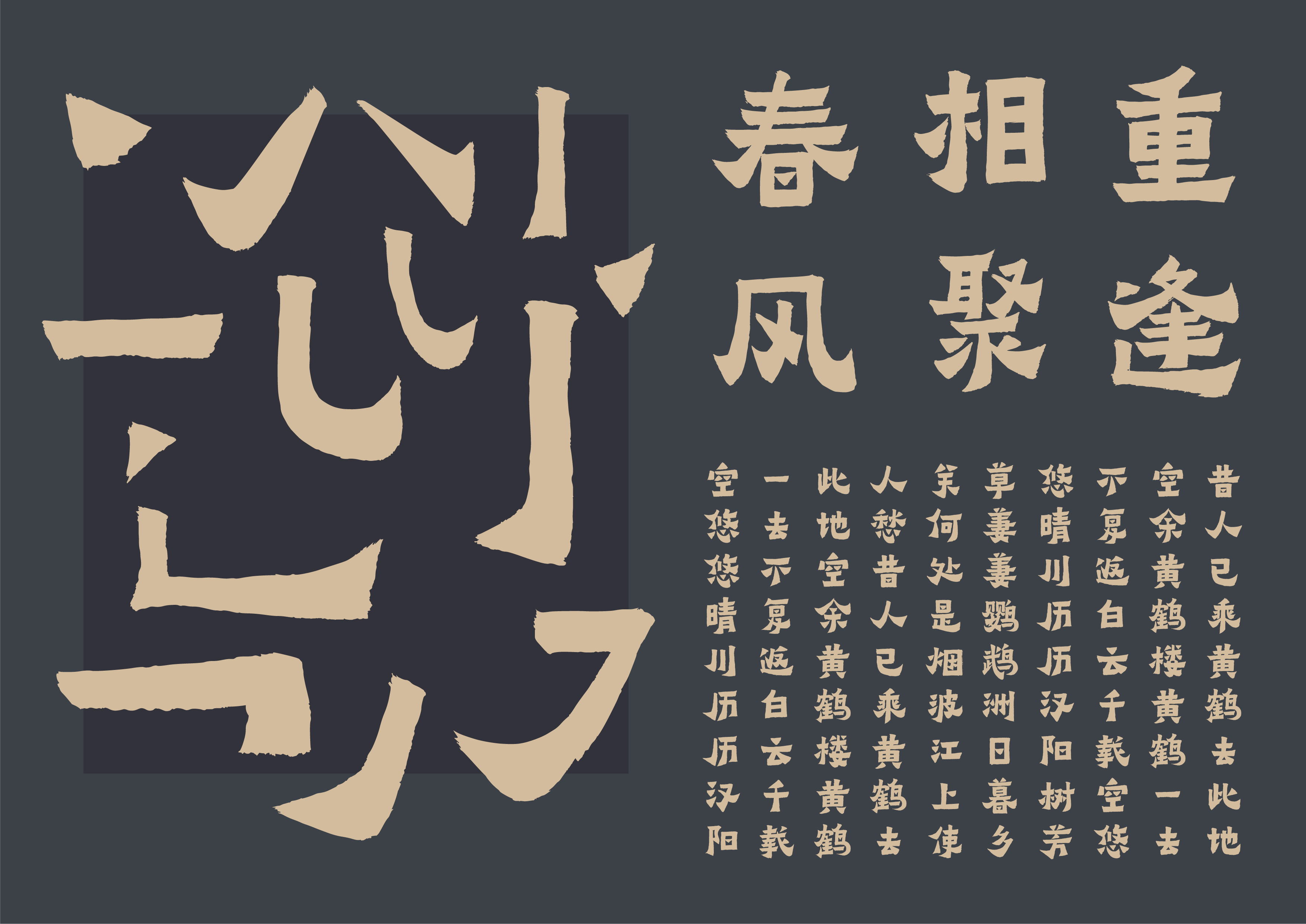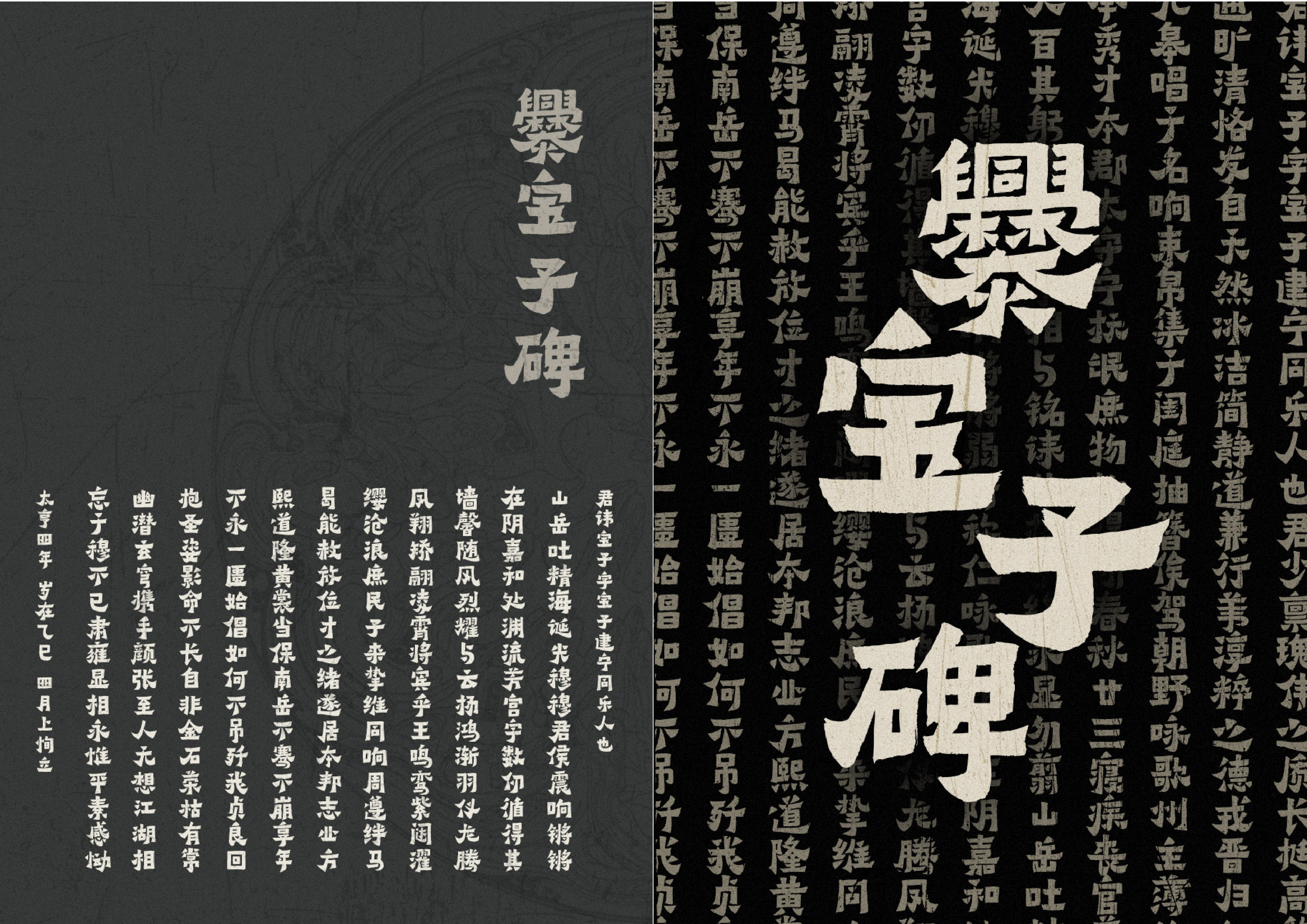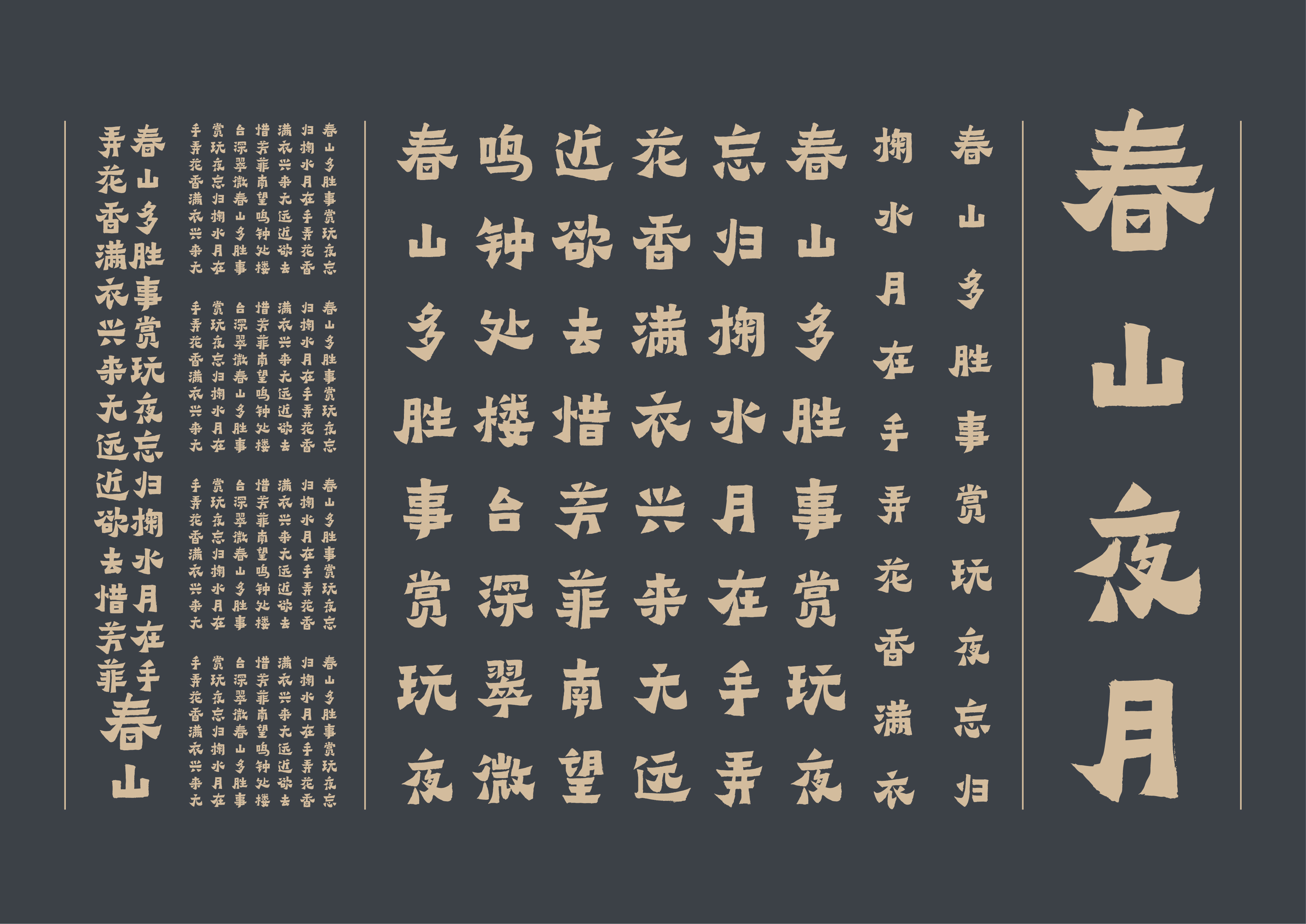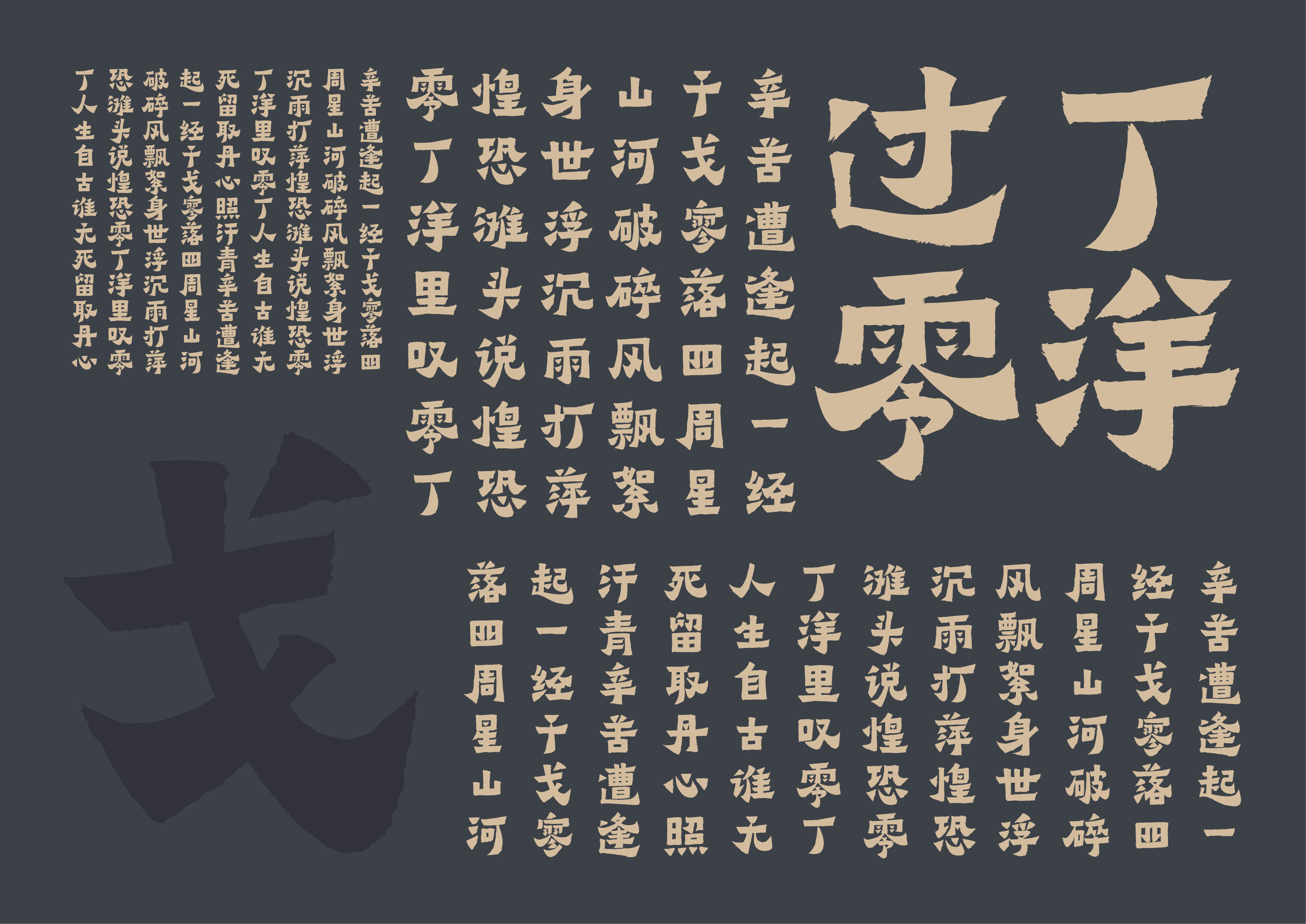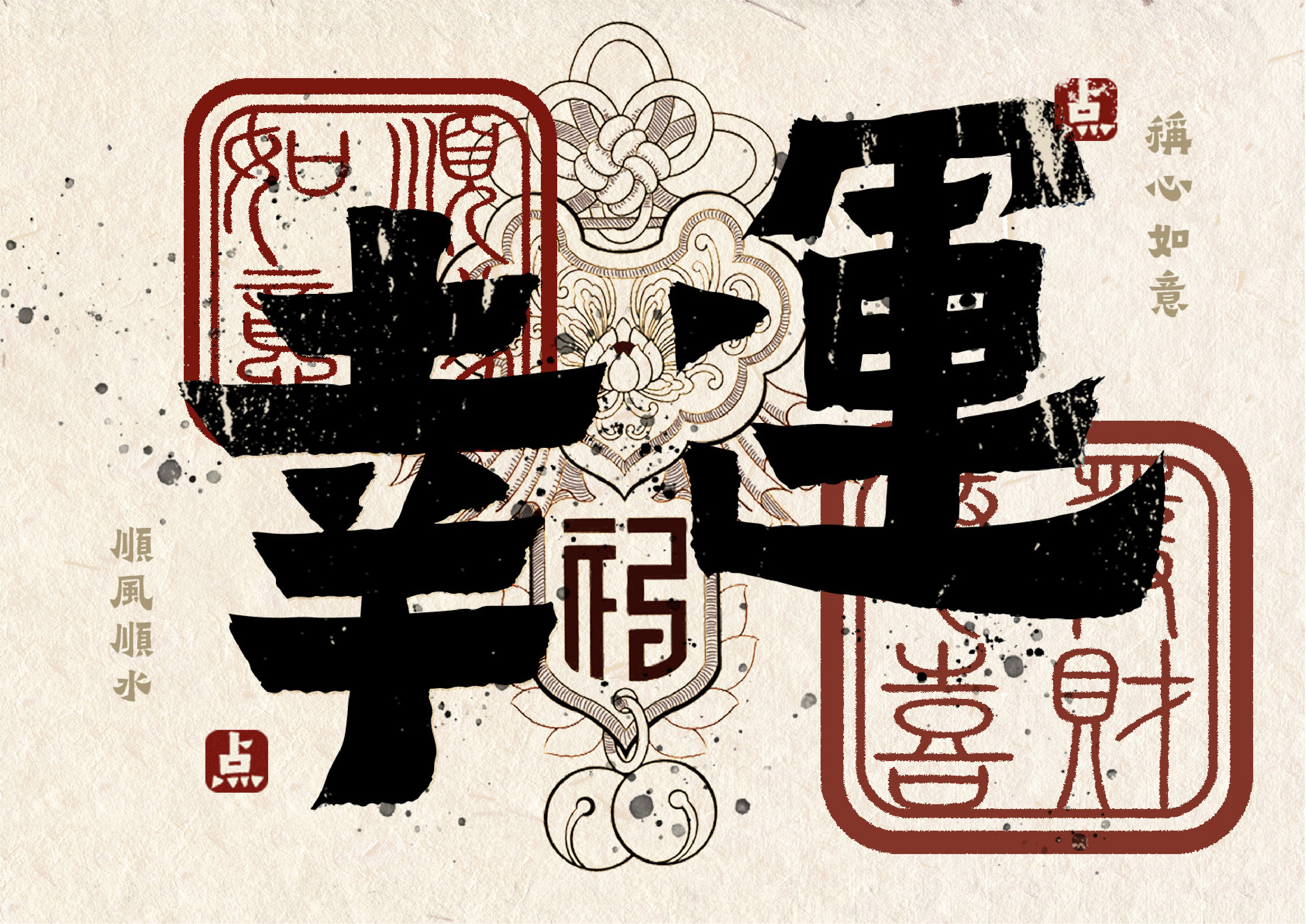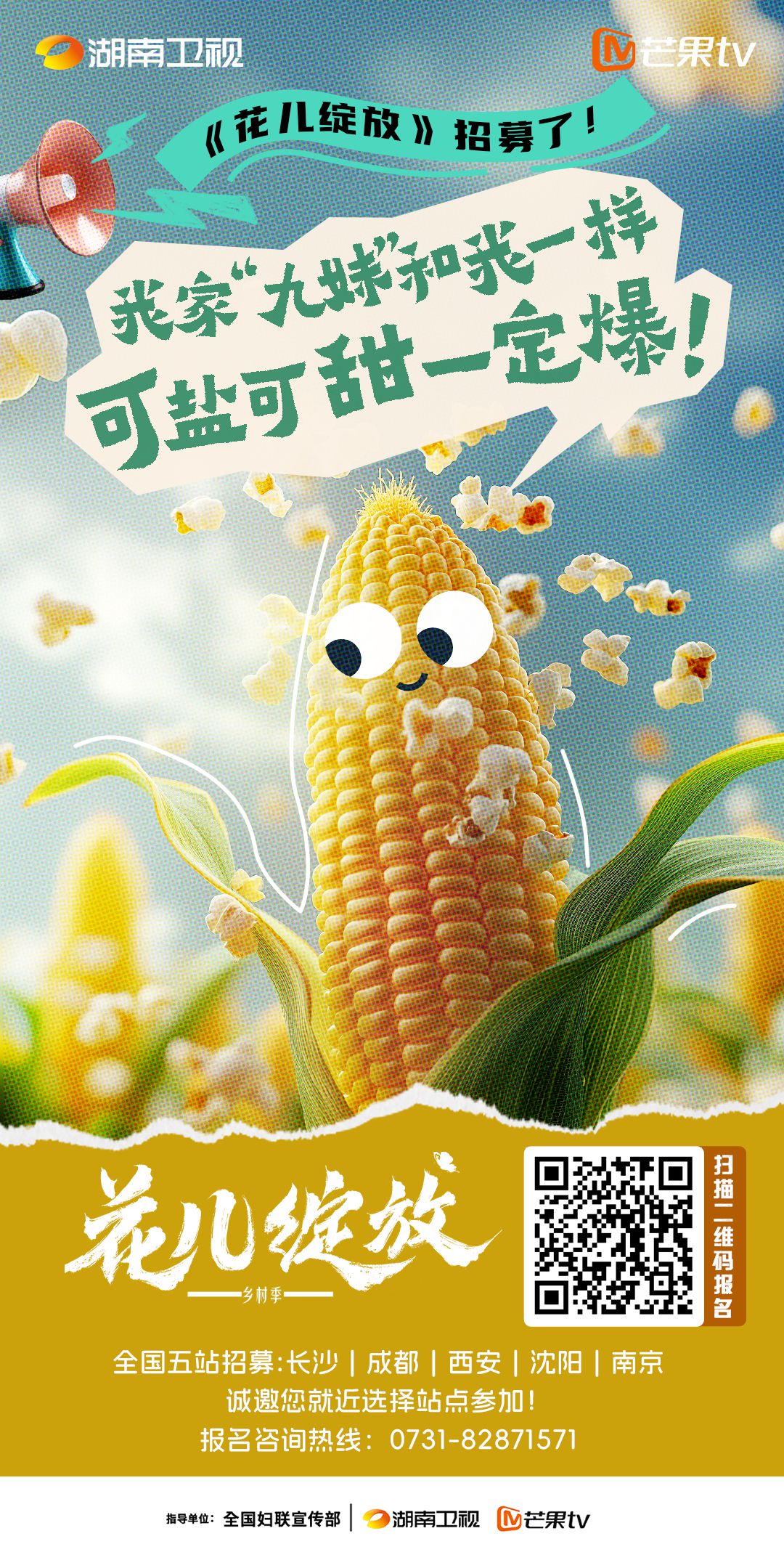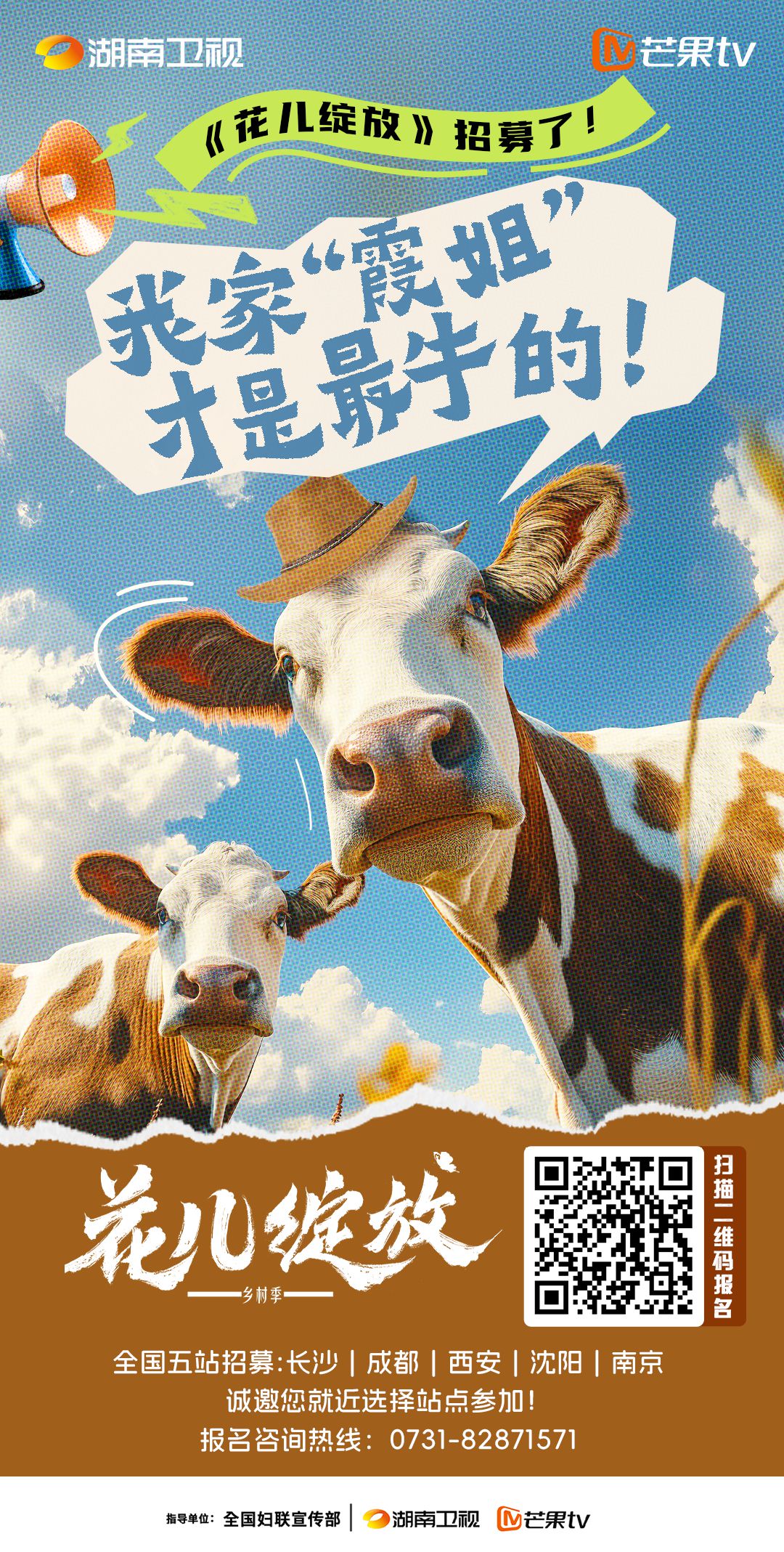
这款又隶又楷的字体,获得金奖!
在字由上有这样一款特别的字体,TA既有隶书蚕头雁尾、一波三折的特色,又如楷书结体规整。
那便是这款以《爨宝子碑》为蓝本复刻的字体——点字爨宝子。
这款字体也在今年荣获了MUSE缪斯国际创意大奖(MUSE Creative Adwards 2024)字体板块的金奖🎉🎉
点字爨宝子从原碑中抽象出笔画的几何形态,字体笔画锐利,字形大小错落,朴茂古厚,大巧若拙,气魄雄强,古韵气质。
看起来还有那么点张扬叛逆。
脱胎于碑刻的书法字体,用在国风场景中那是再合适不过了~
可以用在节气海报上。
也可以烘托传统节日氛围感。
用作综艺海报标题,能展现出十足个性感,金石刻印的质感与撕纸拼贴风格相当搭配。